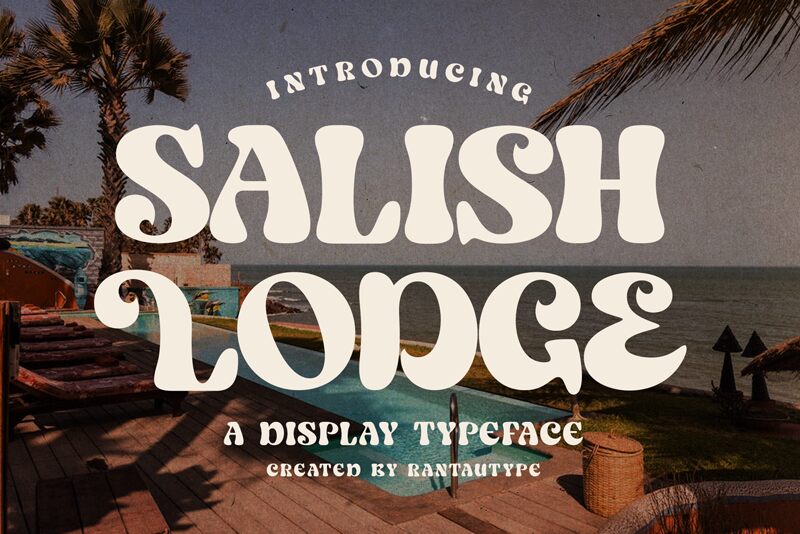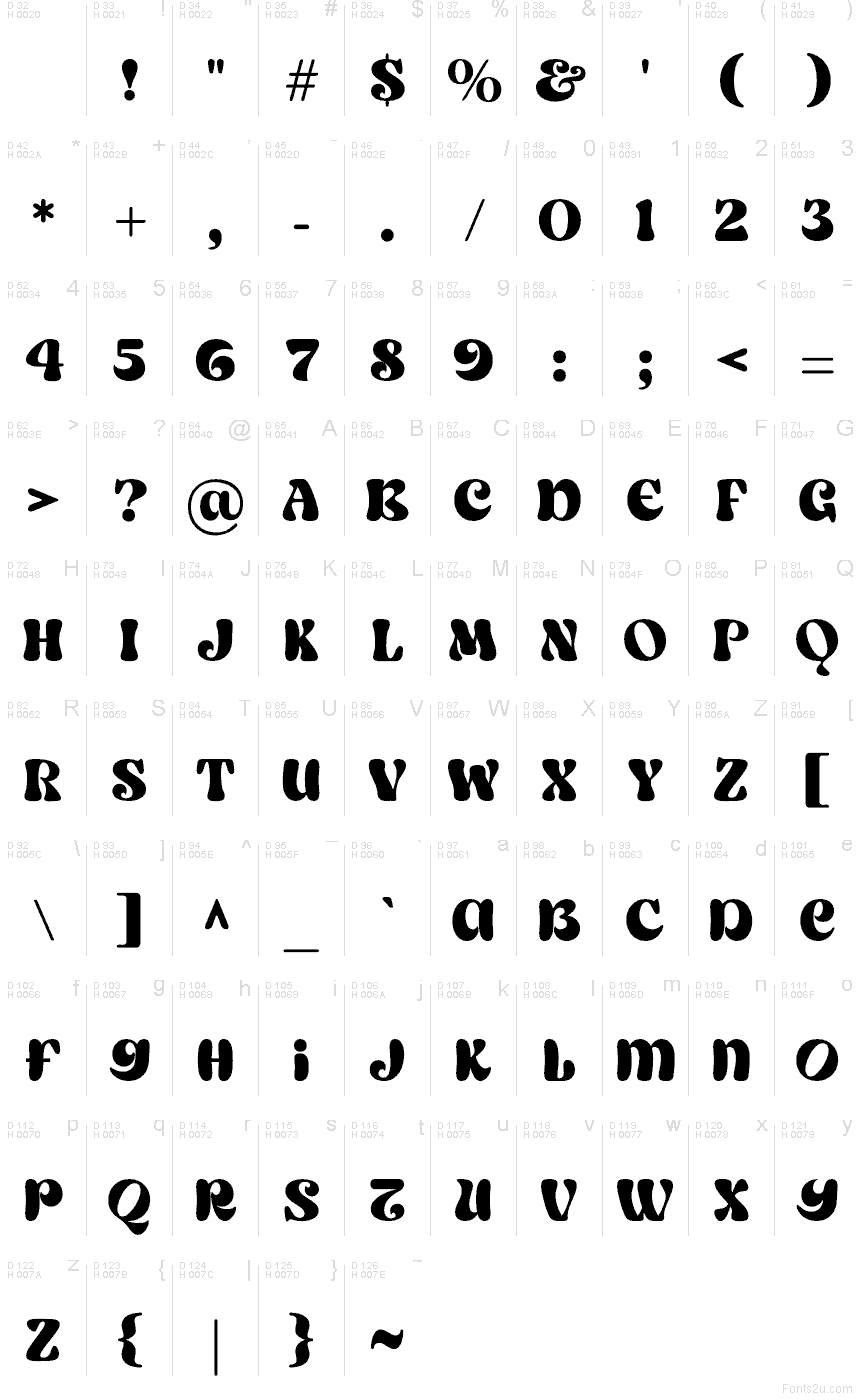
Salish Lodge
Salish Lodge od Rantau Type je bezplatné groovy písmo, ktoré definujú nabobtnalé, zaoblené tvary a hlboko zakrútené konce, ktoré dodávajú písmenám mäkkú siluetu pripomínajúcu lampu s lávou. Rytmus pôsobí husto a dynamicky, so širokými vzpriamenými tvarmi, ktoré sú rozbité vnútornými zárezmi a špirálovitými otočkami, vďaka čomu dizajn nepôsobí stroho.
Táto kombinácia dáva krátkym titulkom silnú úlohu na plagátoch, obaloch inšpirovaných hudobnými nosičmi, v brandingu kaviarní, na letákoch či v návrhoch nálepiek. Písmo sa takisto skvelo hodí na veľké citáty a nadpisy v štýle loga, kde jeho plyšové krivky a zakrútené zakončenia dokážu samy osebe navodiť náladu 70. rokov bez potreby ďalších dekorácií.